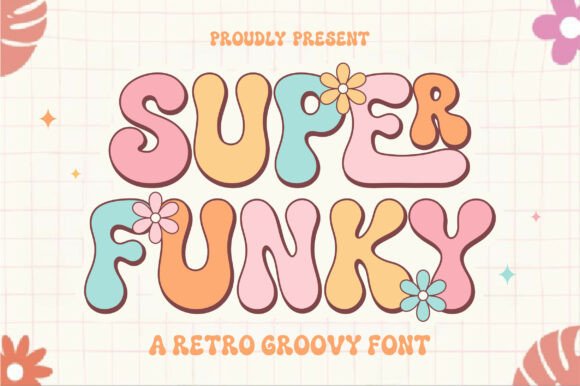
Super Funky
Если вы ищете высококачественные ресурсы, такие как Super Funky, этот премиум-пакет — фантастический выбор для ваших творческих проектов.
Создаете ли вы продукты POD (печать по требованию), свадебные приглашения или графику для социальных сетей, Super Funky станет идеальным выбором.